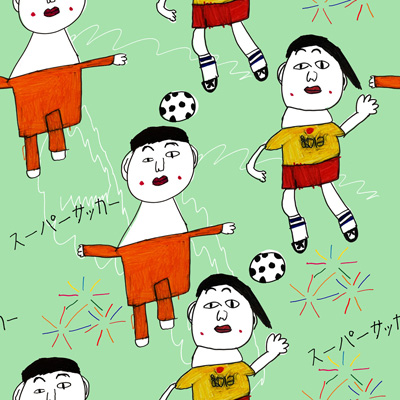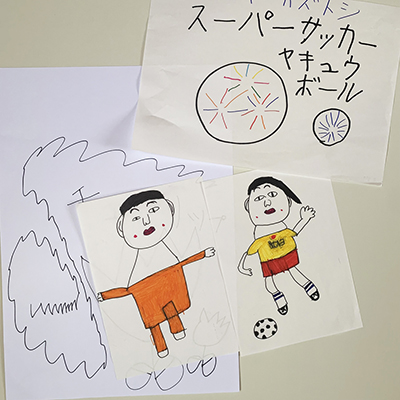
これぞスーパーサッカー!
サッカー!?これはスーパーサッカー!
勝つ時も負ける時もある。ゴールキーパーが上手く取れない時、頑張っているなって思う。サッカーは楽しそう。byM.O スーパーサッカー!by Kazu(M.OとKazuとY.Y)
Kazuさんがサラリと書いた「スーパーサッカー」と、M.Oさんのユーモラスな選手たち、Y.Yさんの勢いある線を組み合わせ、想像を掻き立てるスーパーサッカーに。いつだって想像を超えてくるのが面白い。(Tomomi Sakauchi)
選手たちが勢いよくこちらに向かってきそうな、はたまたダンスをしてるかのような、愉快なパターンです。普段なかなか接点のない3人のコラボレーションがまた楽しい。(玉川福祉作業所)